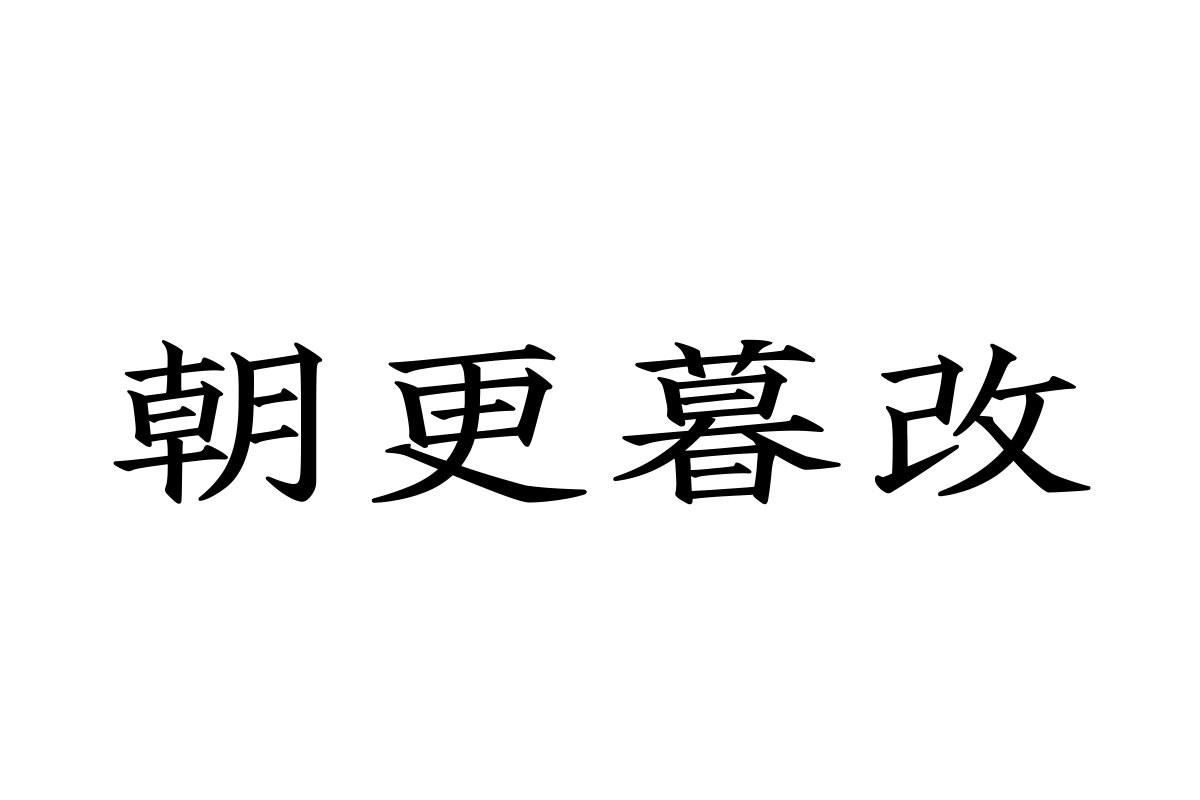
汉仪弦月楷简字体是一款具有现代感的中文书法字体,它以简洁明快的风格和独特的笔画结构吸引了众多设计者的喜爱。这款字体的设计灵感来源于传统的汉字书写艺术,通过简化笔画、优化结构等方式,使得每个字都显得清晰易读,同时也保留了一定的艺术美感。
汉仪弦月楷简字体的特点在于其线条流畅、字形规整,适合用于各种需要展示文字信息的场合。无论是在网页设计、平面设计还是其他视觉传达领域,这款字体都能为作品增添一种独特的文化韵味和现代气息。
总的来说,汉仪弦月楷简字体是一款非常实用的中文字体,它不仅能够提高设计作品的视觉效果,还能够传递出一种简约而不简单的设计理念。